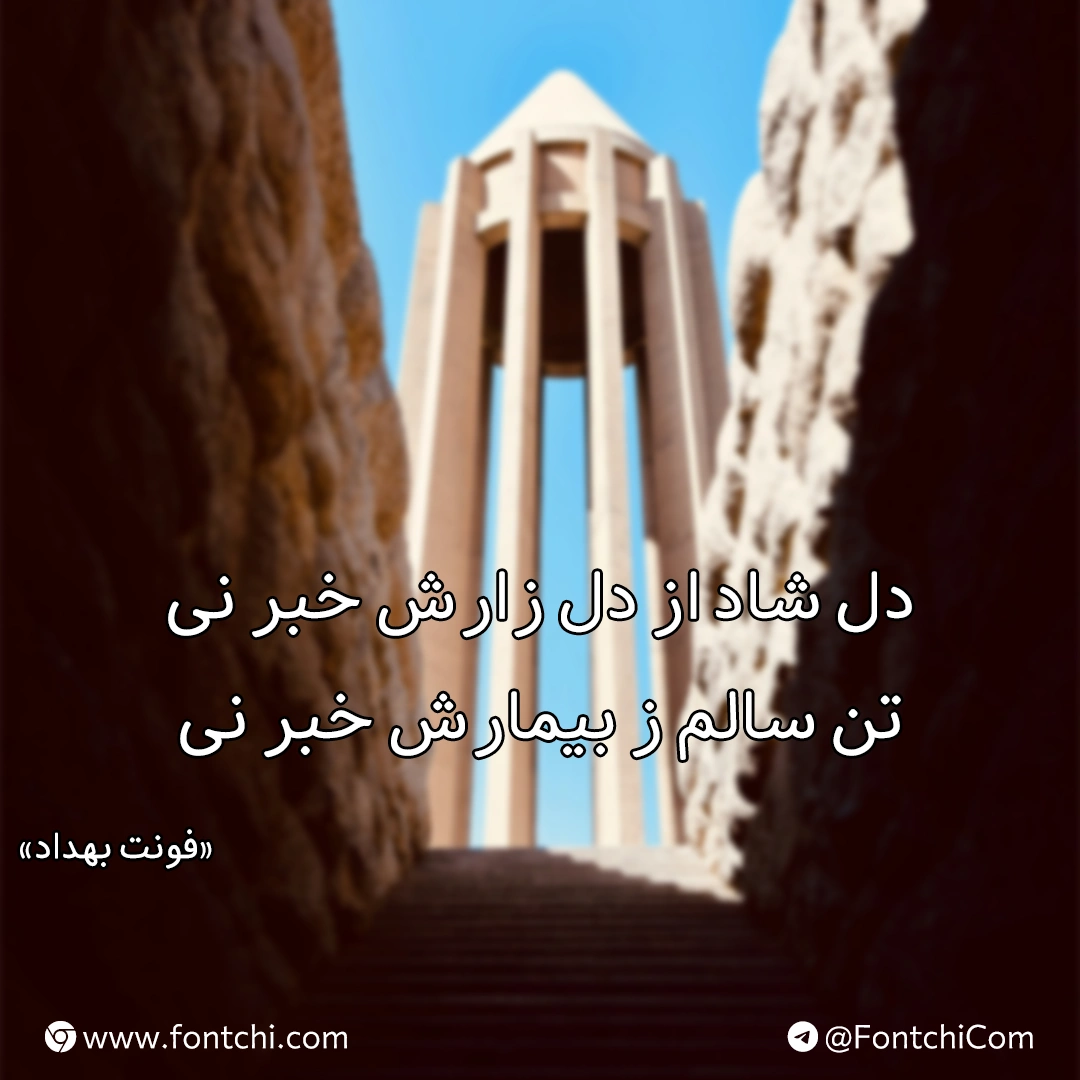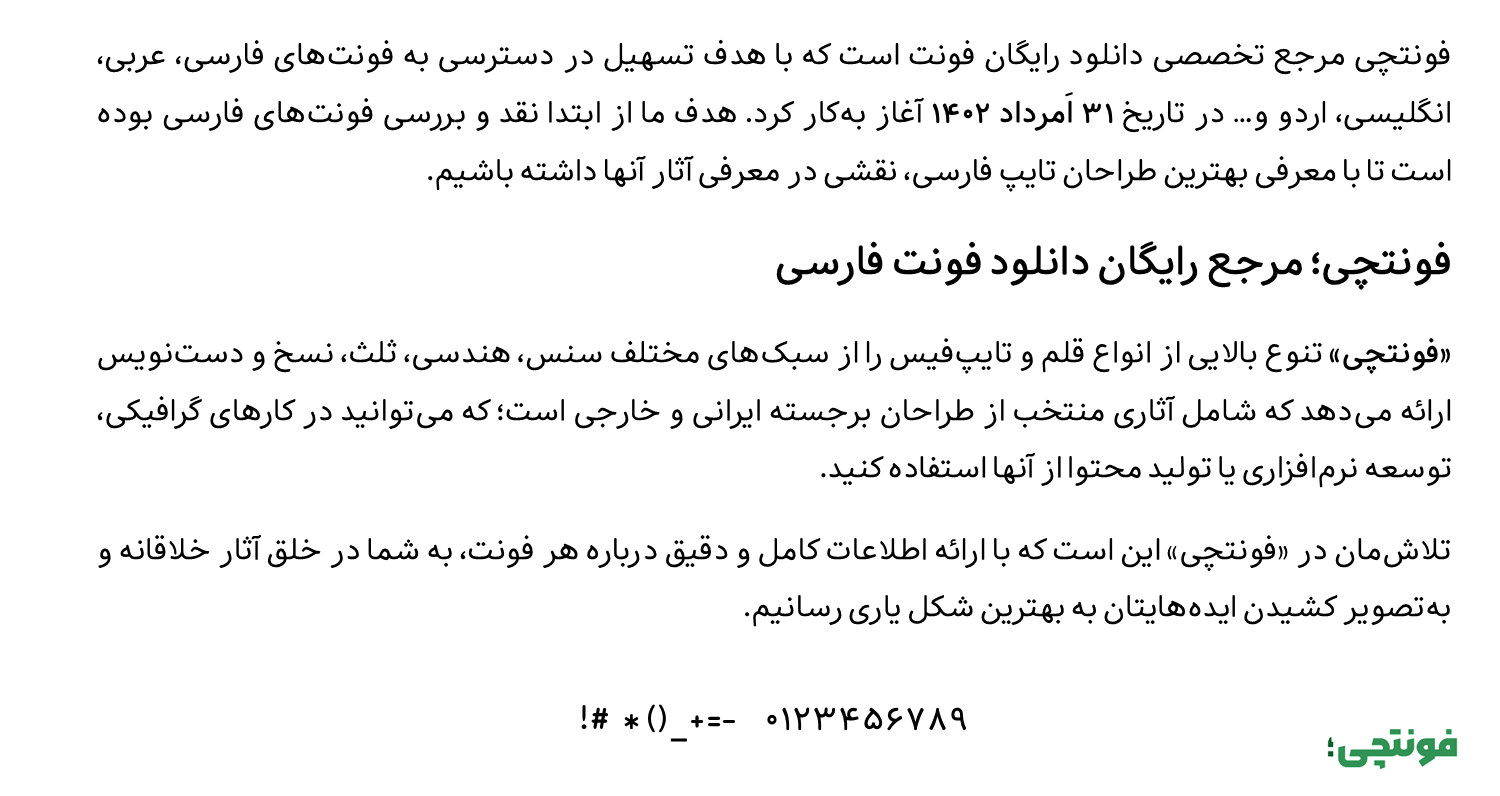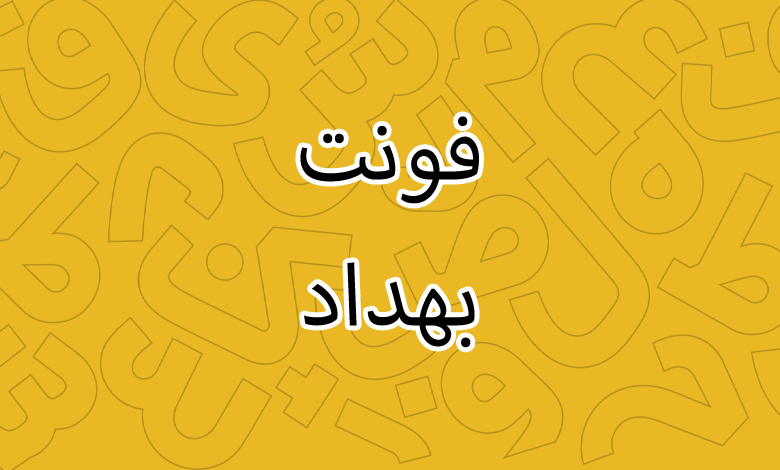
فونت بهداد (Behdad)
نام بهداد
نام نمایشی Behdad
فونت بهداد (به انگلیسی: Behdad) از سری فونت‌های رایگان با پشتیبانی از دو زبان فارسی و عربی است که می‌توانید در پروژه‌هایی که دارای متن طولانی هستند از آن استفاده کنید. این فونت از سبک سنس برخوردار است. در ادامه با بررسی و دانلود فونت بهداد رایگان با شما همراه هستیم.
فونت بهداد توسط صالح سوزنچی در یک وزن معمولی Regular طراحی شده است. نام این فونت از نام یک کودک زنجانی برگفته شده که به‌خاطر علاقه‌ای که این کودک به خط فارسی داشته، نام وی را روی این فونت نهاده است.
فونت رایگان بهداد از زبان فارسی و عربی پشتیبانی کاملی دارد. در زبان فارسی اعداد کاملا فارسی هستند و برای زبان عربی نیز اعداد استاندارد «۰۴۵۶» با ظاهر خود تایپ می‌شوند. این فونت دارای یک نسخه معمولی است که برای استفاده در متون بلند قابل استفاده است.
از کاربردهای این فونت می‌توان به استفاده در مطبوعات، نامه‌نگاری اداری و صنعت چاپ به‌ویژه در حوزه جوانان و نوجوانان اشاره کرد. ظاهر دوستانه این فونت خوانایی بالایی برای متون بلند دارد که می‌تواند در کتاب‌ها و روزنامه‌ها مورد استفاده قرار گیرد.
این فونت فاقد گلیف‌های لاتین است؛ به عبارتی برای زبان‌های غیر از فارسی و عربی نمی‌توانید از این فونت استفاده کنید و لازم است که فونت جایگزینی برای آن داشته باشید. می‌توانید از فونت وزیرمتن که آن هم یک قلم آزاد است استفاده کنید.
سبک فونت بهداد سنس است. منحنی‌ها از ترکیب دایره و بیضی تشکیل شده‌اند که ظاهری دوستانه به این قلم داده است. همچنین دندانه‌ها در برخی نقاط دارای ظاهری مورب هستند تا شکل فونت را نمایشی‌تر کنند.چشمی‌ها در حروفی مثل «م، ه» نیز دارای ظاهری ۳ گوش اما اندازه کوچک هستند.
با اینکه فونت بهداد از زبان انگلیسی پشتیبانی نمی‌کند، اما می‌توان از این قلم به‌صورت ترکیبی برای سایت یا اپلیکیشن موبایل استفاده کرد که بخواهیم فونت لاتین را از یک قلم دیگر استفاده کنیم.